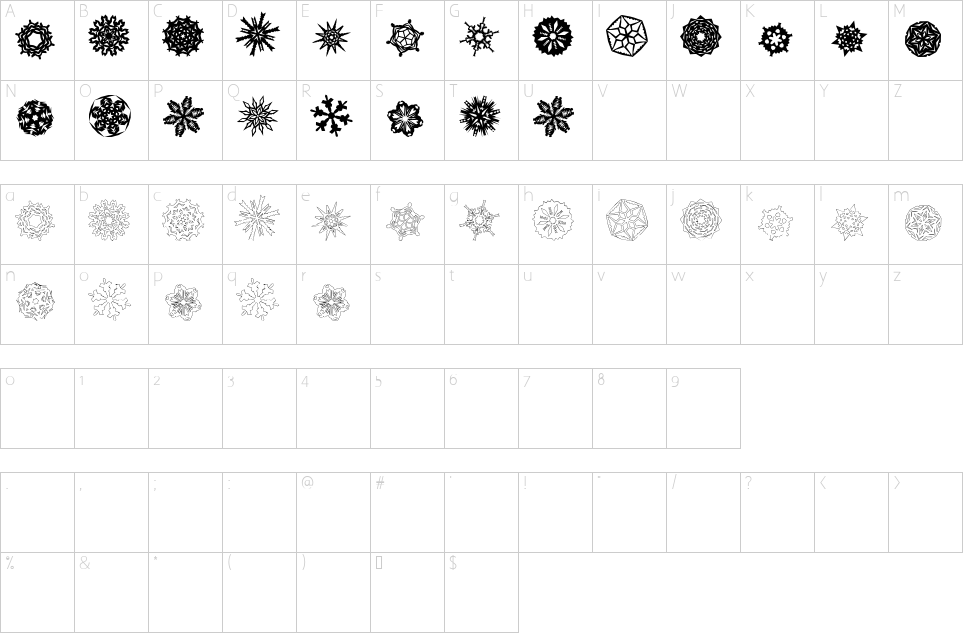
Descubra uma fonte única e encantadora chamada Paper Snowflakes, dedicada à categoria de fontes gratuitas. Esta elegante fonte, criada por Shara Weber, transmite uma sensação de delicadeza e pureza que se destaca na sua categoria. Com seu design minimalista, Paper Snowflakes é uma opção perfeita para estilos de design que valorizam o simples e o belo. Seja para criações de logotipos, texturas de arte, ou simplesmente para adicionar um toque agradável a qualquer projeto, Paper Snowflakes oferece uma versatilidade que vai do simples ao sofisticado. Essa fonte foi um dos mais baixados, com mais de 25.000 downloads, evidenciando sua popularidade entre os designers. Se você está procurando por uma fonte que traga uma dose de encanto ao seu design, Paper Snowflakes está definitivamente no seu radar. Descubra mais sobre esta fonte encantadora e instale-a em seu projeto agora.